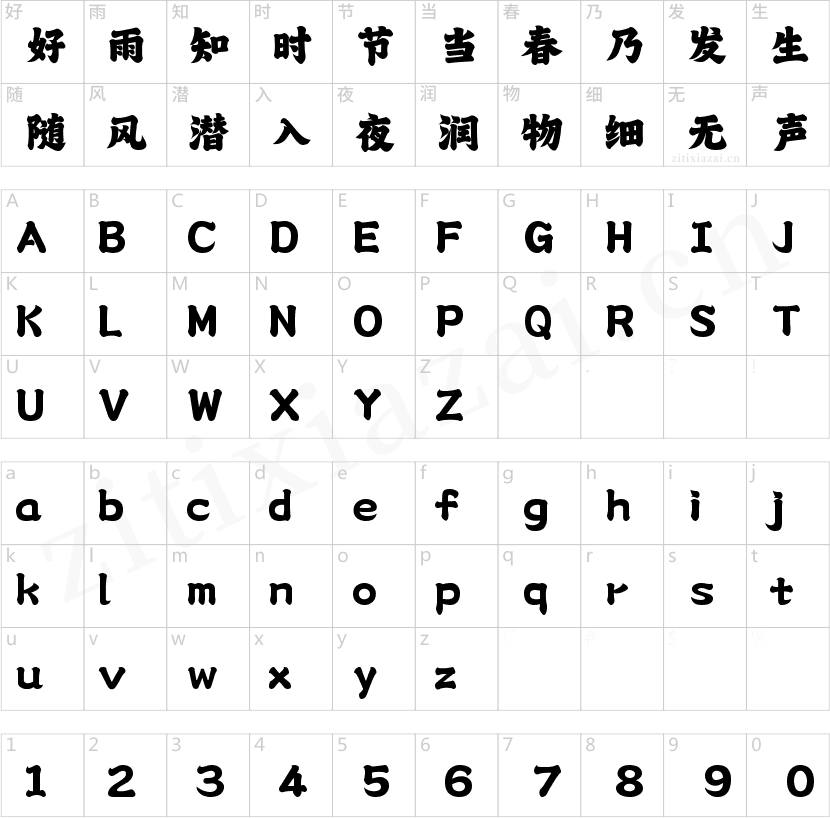
字魂271号-王朝体
字魂字体字魂王朝体字体是由字魂创意字库设计并生产的一款可商用的字体,被收录于华夏王朝系列。该字体支持GB-2312标准以及最新的字魂ZH7144标准,包含7144个中文、字母、符号和数字,字体类型偏向楷体,具有力量、豪放、中国风、帅气的风格,在市面上广泛用于广告、标题、媒体&H5等场景。